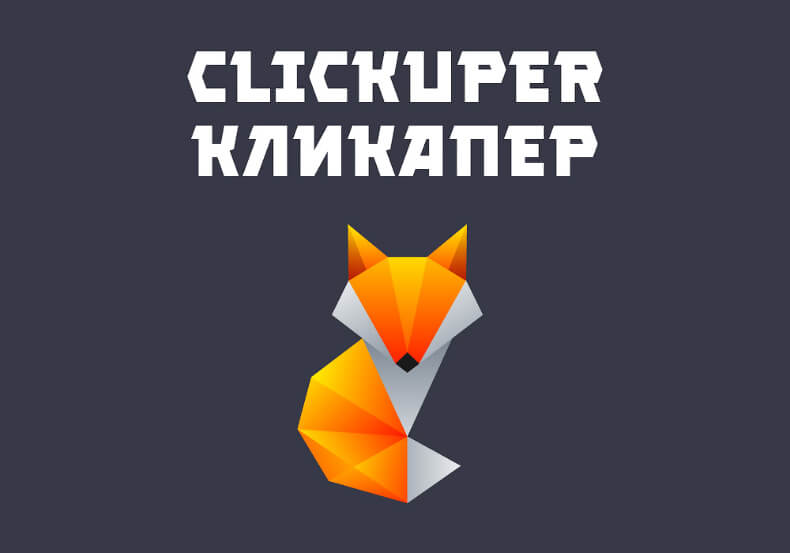
Шрифт - Кликапер/Clickuper
Суровый кириллический шрифт с поддержкой латиницы, который отличается декоративными засечками и крупными символами. Шрифт отлично подойдёт для создания броских заголовков и текстов, которые точно заметят и обратят на них внимание. Используйте в дизайне, медиа и любых других проектах.